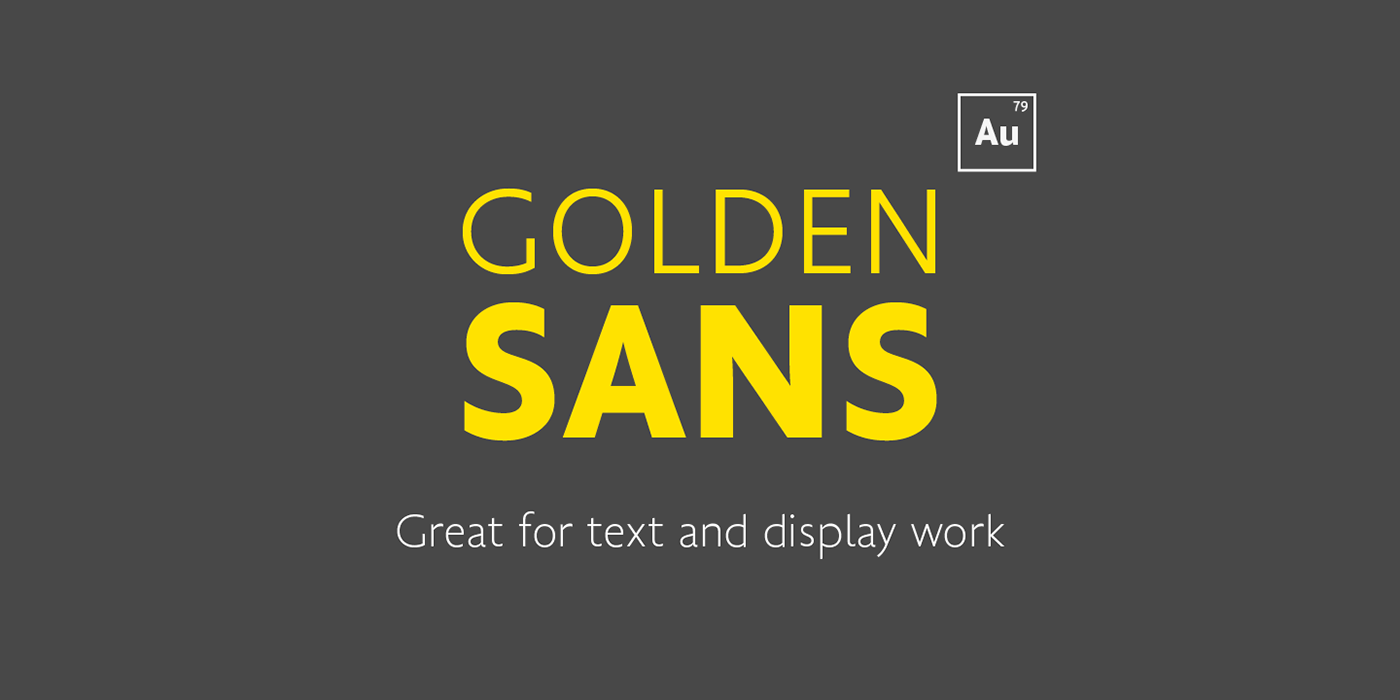
Golden Sans Font
A Golden Sans Font é uma escolha perfeita para designers modernos que buscam alegria no design. Com seu elegante formato livre de serif, ela oferece uma variedade impressionante de sete estilos, cada um com um tom único e sofisticado. Essa fonte foi criada pelo designer Hamilton e está disponível em versão profissional na MyFonts pela empresa Artill Typs. Uma das vantagens da Golden Sans é sua qualidade moderna e extremamente refinada, que a torna adequada para uma ampla variedade de projetos gráficos, desde logos e anúncios até design editorial e materiais educacionais. Se você está buscando um recurso gráfico com profundidade e sutileza, a Golden Sans pode ser a escolha certa para trazer personalidade e estilo à sua próxima criação visual.